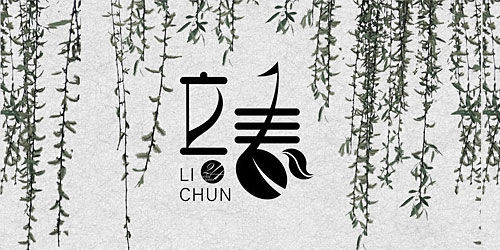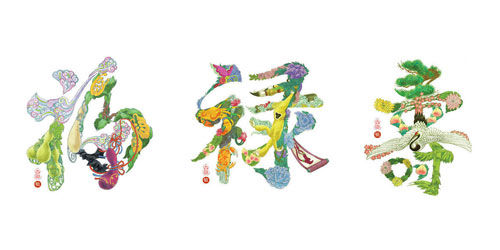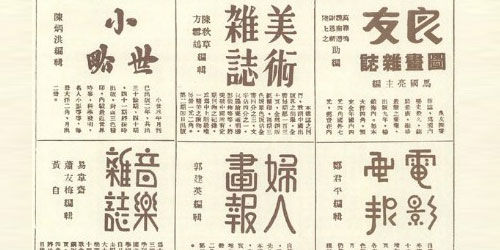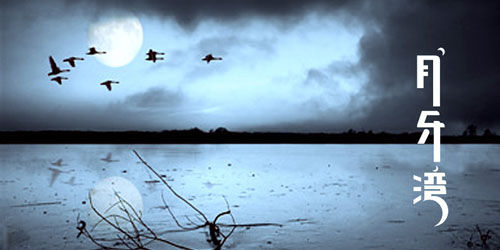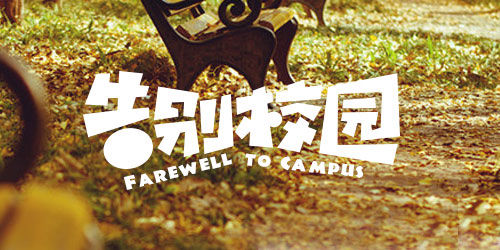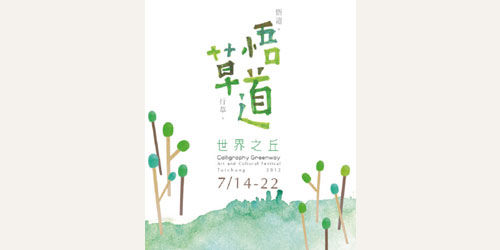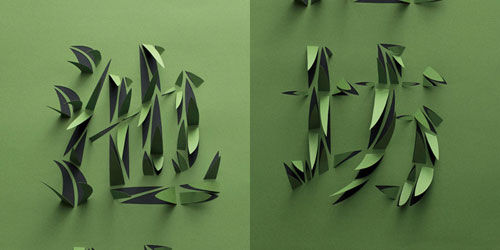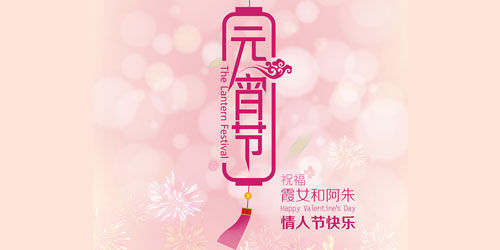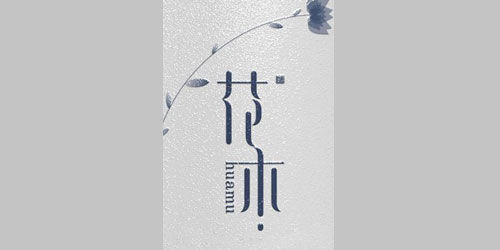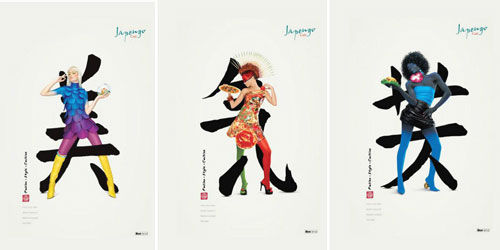
三十五个不同风格的中文字体设计作品欣赏
立春
35个风格迥异的中文字体设计作品欣赏
福绿寿
35个风格迥异的中文字体设计作品欣赏
怀旧字体
35个风格迥异的中文字体设计作品欣赏
月牙湾
35个风格迥异的中文字体设计作品欣赏
告别校园
35个风格迥异的中文字体设计作品欣赏
悟草道
35个风格迥异的中文字体设计作品欣赏
池坊
35个风格迥异的中文字体设计作品欣赏
元宵节
35个风格迥异的中文字体设计作品欣赏
花木
35个风格迥异的中文字体设计作品欣赏
时尚的人物与字体结合设计
35个风格迥异的中文字体设计作品欣赏
七月十四
35个风格迥异的中文字体设计作品欣赏
花开半夏
35个风格迥异的中文字体设计作品欣赏
水心
35个风格迥异的中文字体设计作品欣赏
早安、晚安
35个风格迥异的中文字体设计作品欣赏
立春
35个风格迥异的中文字体设计作品欣赏
姑娘
35个风格迥异的中文字体设计作品欣赏
十二生肖形状字体设计
35个风格迥异的中文字体设计作品欣赏
石上花开
35个风格迥异的中文字体设计作品欣赏
城市求生
35个风格迥异的中文字体设计作品欣赏
清风轩
35个风格迥异的中文字体设计作品欣赏
纯水
35个风格迥异的中文字体设计作品欣赏
多个不同配色的字体设计
35个风格迥异的中文字体设计作品欣赏
新生
35个风格迥异的中文字体设计作品欣赏
路
35个风格迥异的中文字体设计作品欣赏
生日快乐字体设计
35个风格迥异的中文字体设计作品欣赏
字体设计:爱如空气
35个风格迥异的中文字体设计作品欣赏
字体设计:雨水、惊蛰、清明
35个风格迥异的中文字体设计作品欣赏
字体设计:唐、宋、元
35个风格迥异的中文字体设计作品欣赏
电影海报中的字体设计
35个风格迥异的中文字体设计作品欣赏
字体设计:简贝
35个风格迥异的中文字体设计作品欣赏
字体设计:菜鸟
35个风格迥异的中文字体设计作品欣赏
字体设计:时光轴
35个风格迥异的中文字体设计作品欣赏
字体设计:一石二鸟
35个风格迥异的中文字体设计作品欣赏
前期我们整理了很多英文的字体设计作品,虽然只有26个字母,但却能设计很多很多创新的字体出来。其实中文字体也是可以设计多样化的,今天达人主要精选了2013年最新的中文字体设计作品,有中国风、可爱风、复古风等等,我想这么些作品中肯定有设计师们获得灵感和值得学习的地方,Enjoy!